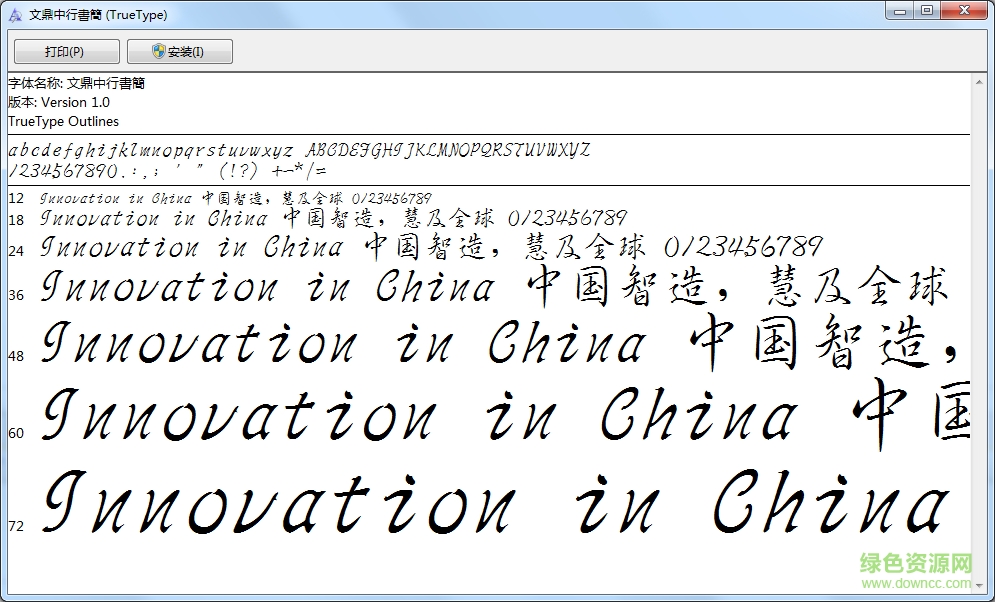
軟件介紹 軟件標簽: 文鼎中行書 文鼎字體 文鼎中行書簡字體是一款非常好看的文鼎字體,配以行書的獨特風格,別有一番風味,支持中英文和阿拉伯數(shù)字,此版為簡體版,更符合用戶習慣,歡迎大家下載使用!文鼎中行書簡字體安裝方法第一種 1.下載字體并解壓縮; 2.開始中打開控制面板; 3.在控制面板中打開字體文件夾; 4.把下載的字體復制到此文件夾下; 5.文字添加完成 第二種 1.下載字體并解壓縮; 2.把文件根目錄下的字體壓縮包解壓縮; 3.把文件根目錄下的安裝字體.bat放到含有字體文件的文件夾中,雙擊安裝字體.bat軟件; 4.文字添加完成 軟件截圖 上一張下一張(1 / 1) 安裝詳細截圖 猜你喜歡 行書字體 行書字體 行書字體包括了鋼筆字行書字體大全、硬筆行書字體等,是一種介于楷書和草書之間的字體。為什么這樣說?因為行書字體既有草書的流暢感,又有楷書的端正感,可以說,行書結合了草書和楷書的特點,形成了獨特好看的行書字體。喜歡的朋友,趕快下載體驗吧! 查看更多>> 繁體行書字體 9.76M/中文/4.0/免費版下載 winman tun10011字體 17.57M/中文/6.6/下載 南構嘉飛行書字體 10.00M/中文/6.6/下載 c g流麗行書體繁/簡 4.39M/中文/5.0/下載 北方行書簡體 2.63M/中文/7.2/下載 qxyingbixing 1.26M/中文/8.0/下載 其他版本下載 標題 大小 更新日期 下載 下載地址 電腦版 文鼎中行書簡樣式ttf 點擊報錯 軟件無法下載或下載后無法使用,請點擊報錯,謝謝! 關閉報錯反饋 請描述您所遇到的錯誤,我們將盡快予以修正,謝謝! *必填項,請輸入內容 本類最新 文鼎霹靂繁體字體 文鼎妞妞字體 文鼎cs魏碑簡 文鼎cs粗圓繁ttf 文鼎cs大黑繁體 文鼎cs舒同體繁字體 相關文章 修改外部鏈接,email鏈接,pdf鏈接的CSS樣式代碼 Photoshop中制作多種樣式網(wǎng)格背景圖案 XHTML+CSS:調用樣式表 用戶評論 熱門評論 最新評論 發(fā)表評論 查看所有評論(0) 昵稱: 請不要評論無意義或臟話,我們所有評論會有人工審核. 字數(shù): 0/500 (您的評論需要經(jīng)過審核才能顯示)